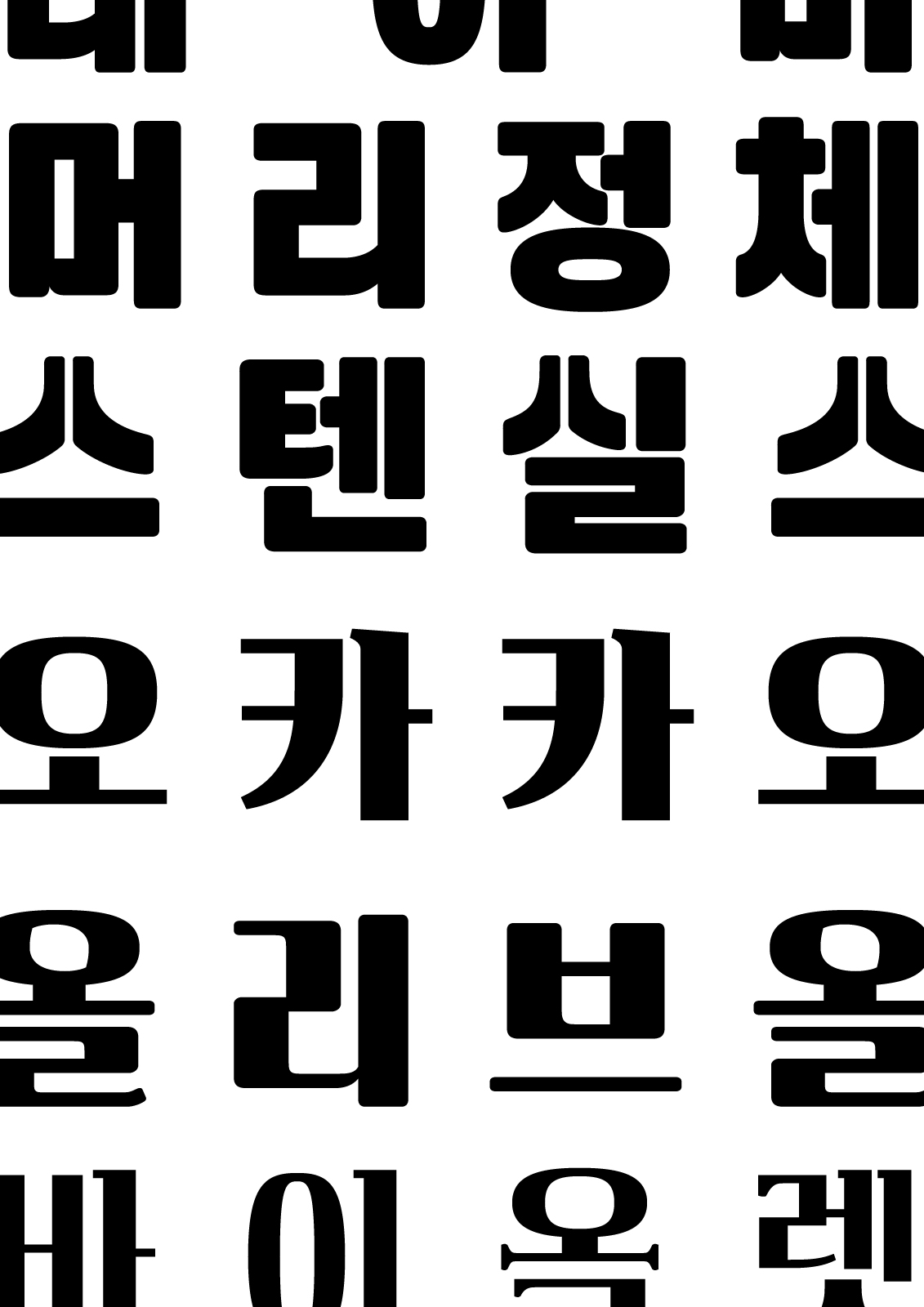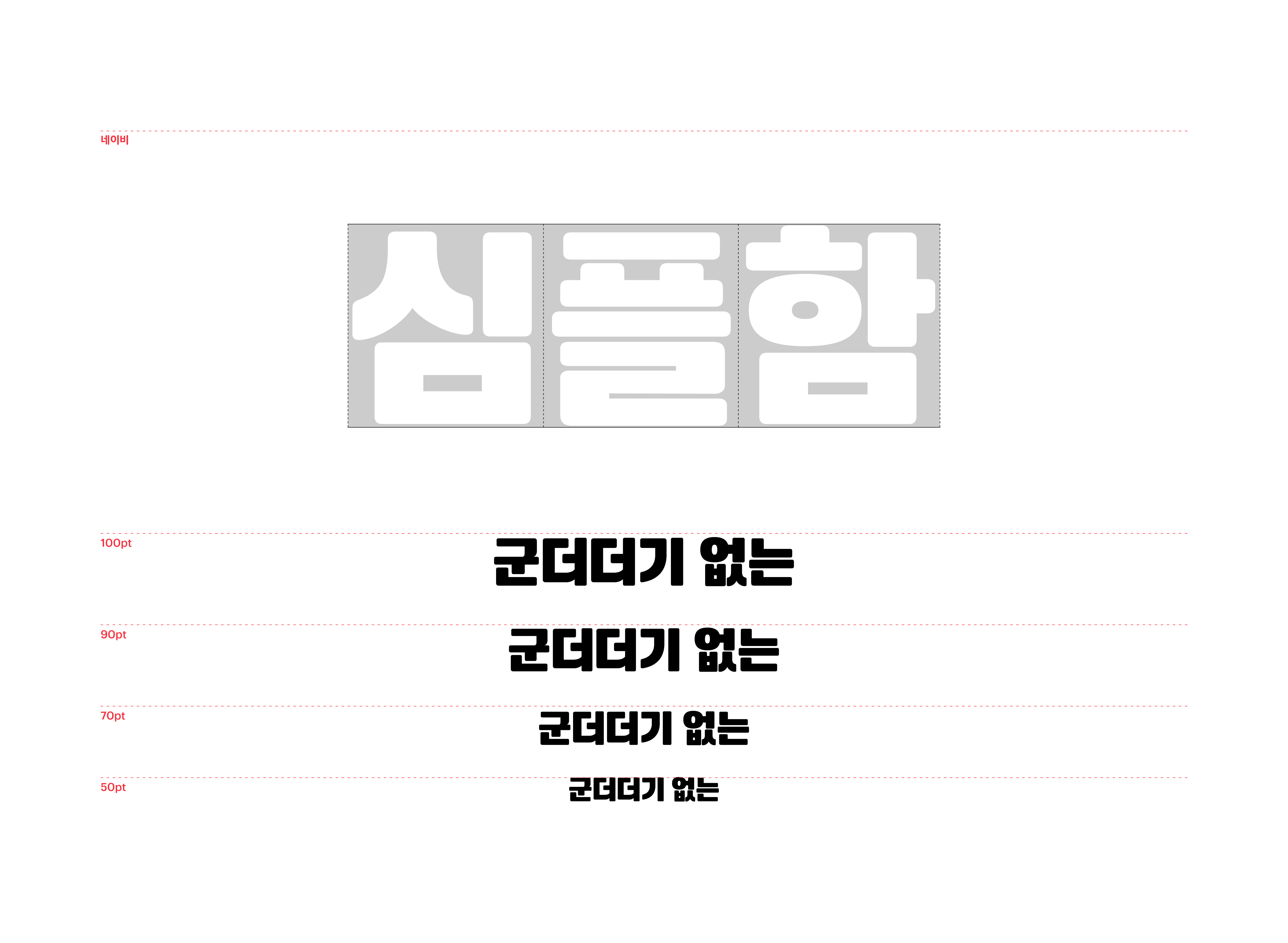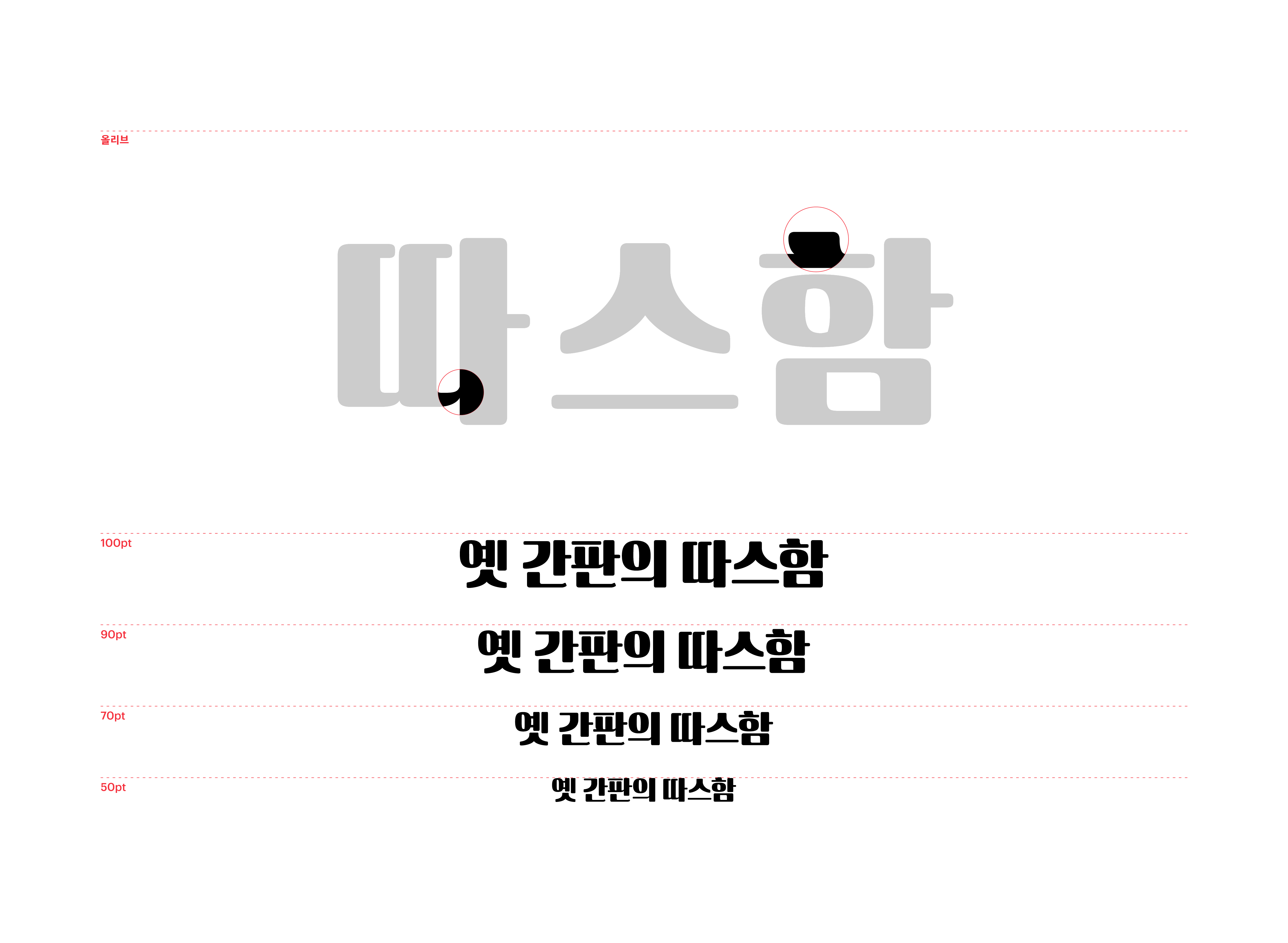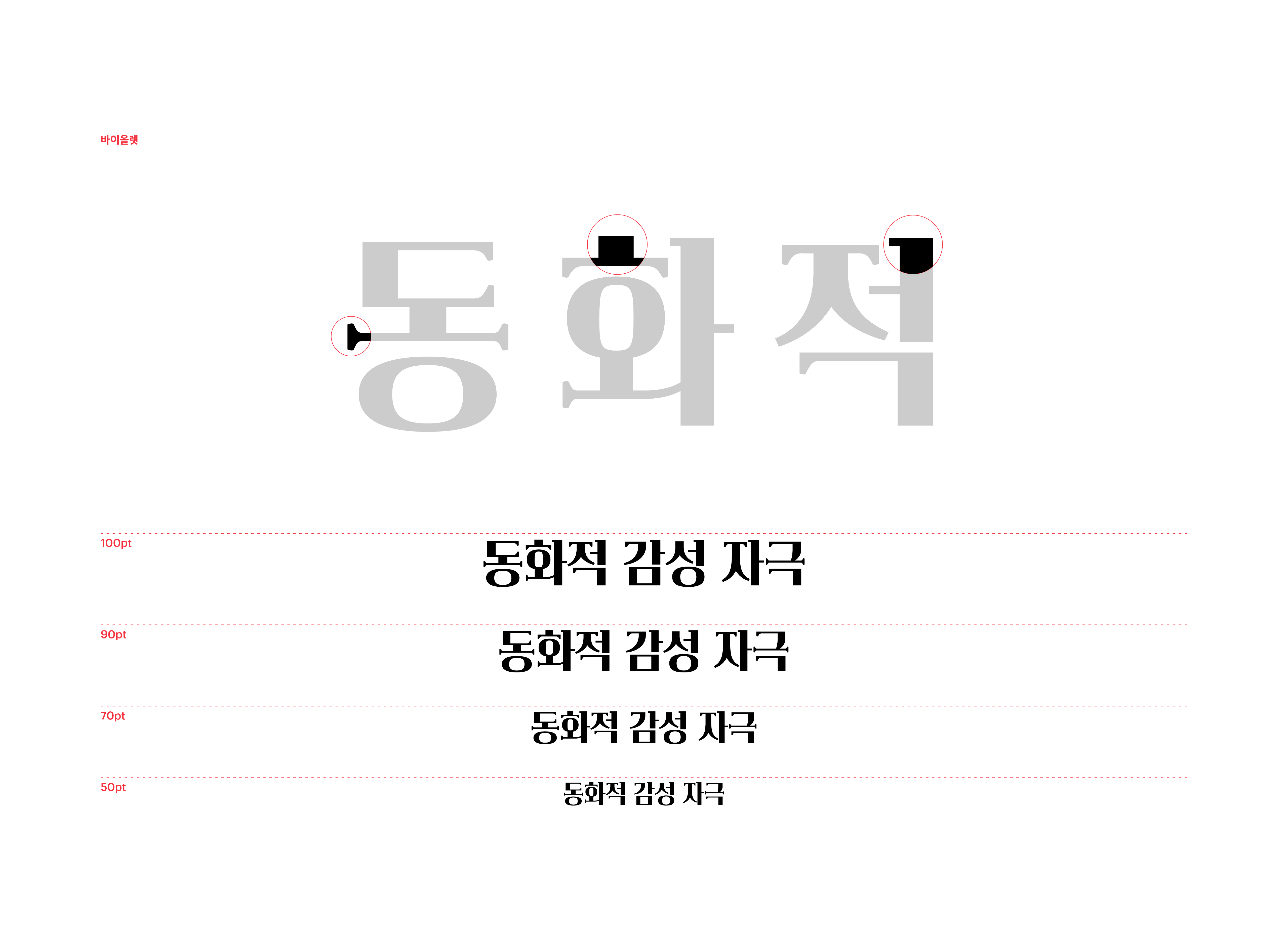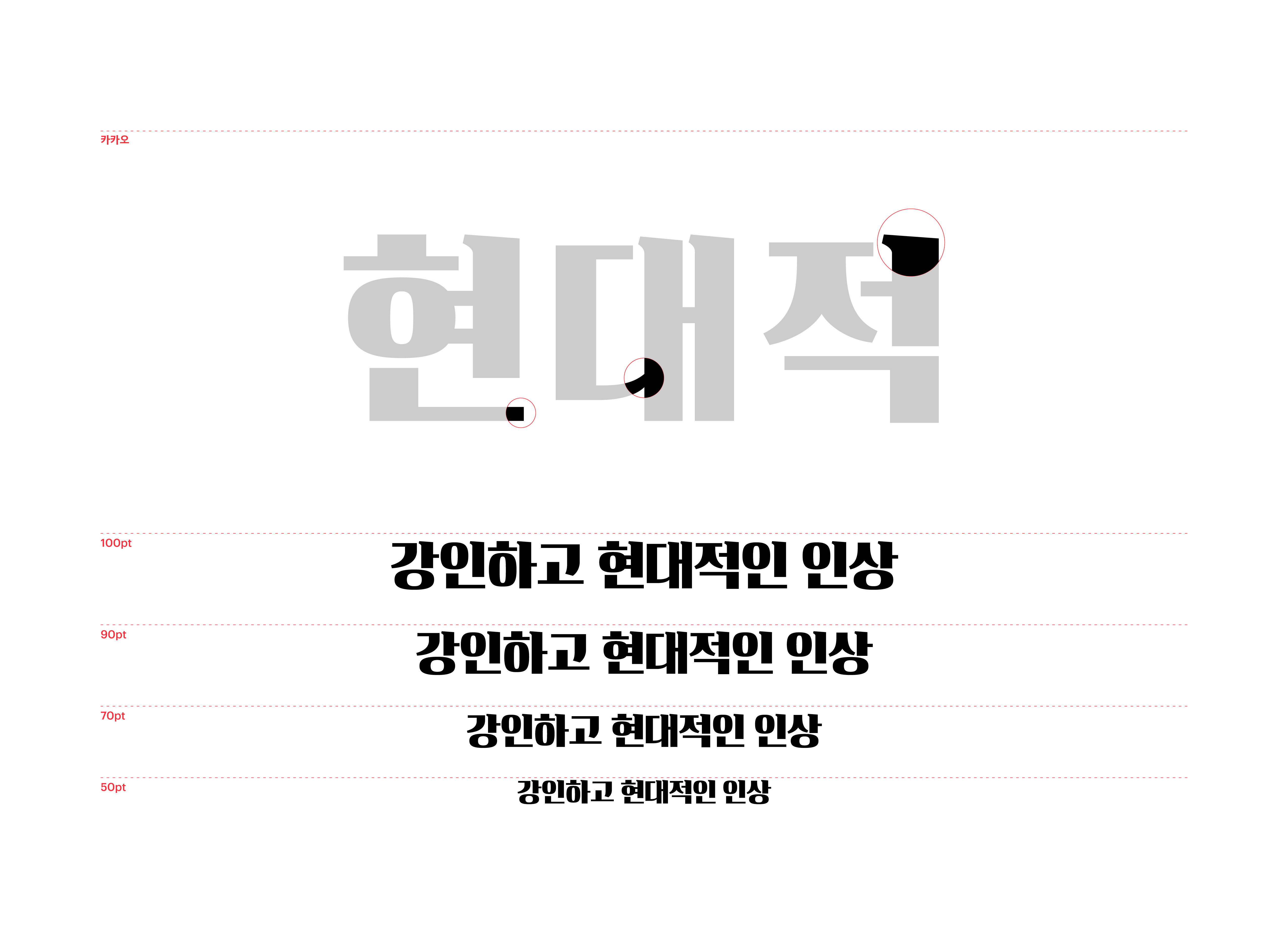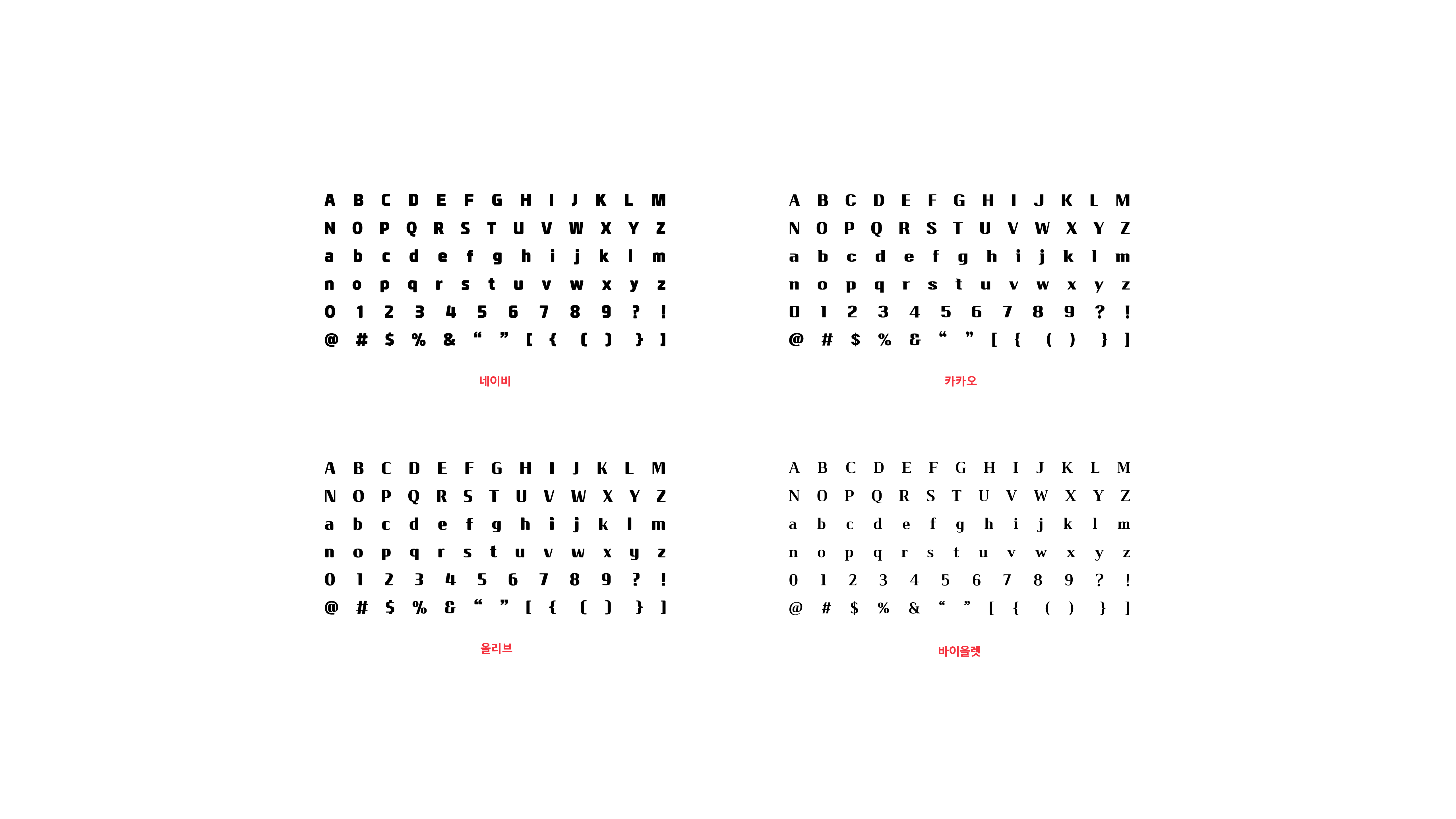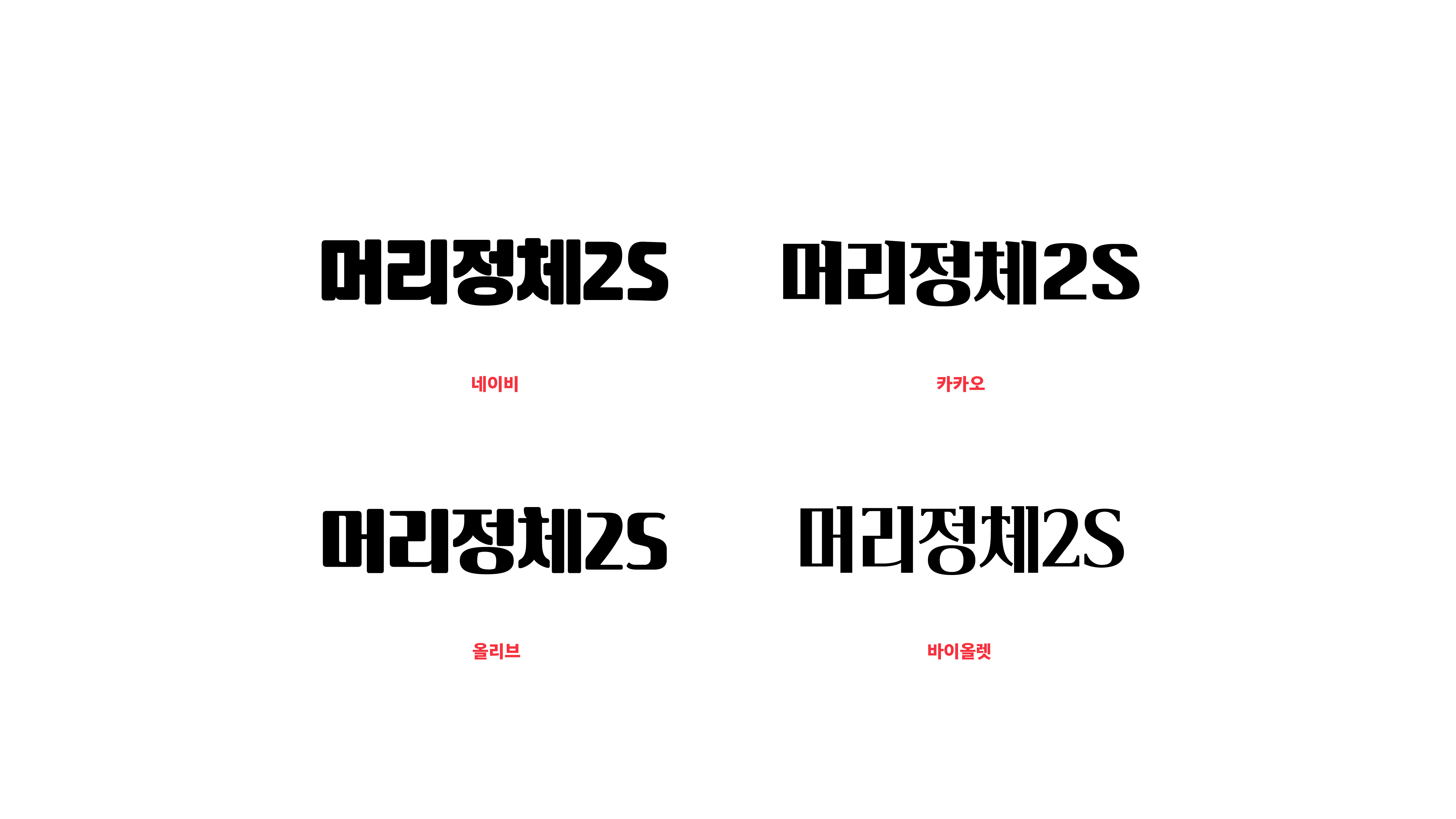
머리정체 2S
Yoon 머리정체 2S
군더더기 없는 심플함을 지닌 네이비, 색다른 세리프로 동화적 감성을 자극하는 바이올렛, 옛 간판의 따스함을 간직한 올리브, 강인하면서도 현대적인 인상을 지닌 카카오. 머리정체2의 기본 골격에 각기 다른 개성을 입힌 특별한 글자 가족이 왠지 끌리는 제목, 치명적인 제목 표현의 세계를 열어갑니다.